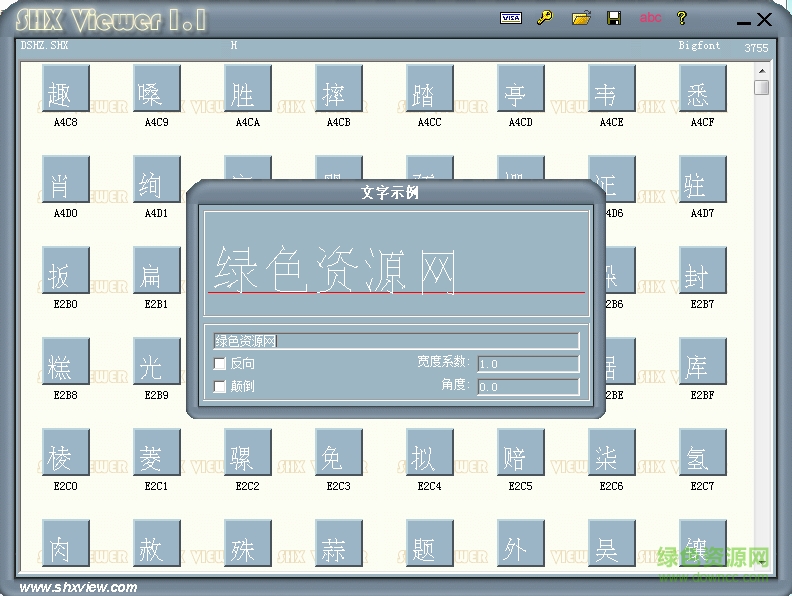
dshz.shx是一款擁有3755個漢字的cad大字體,字形簡潔偏小,連貫醒目,有著清晰的識別性和舒適的閱讀體驗,喜歡的朋友來綠色資源網(wǎng)免費下載吧!
DSHZ.SHX是常見的cad字體,支持中文輸入,字體庫比較豐富,字形大方娟秀有著極佳的書寫美感,適用于平面設(shè)計、文字標記等諸多方面。